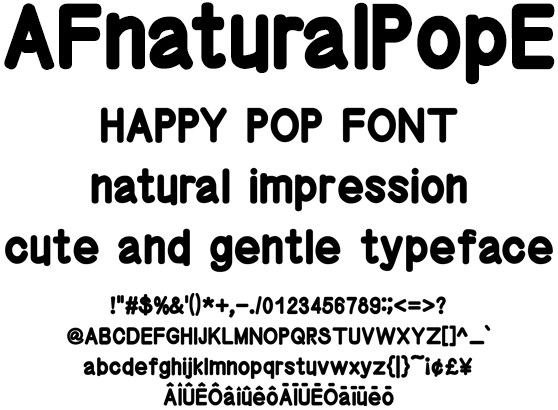
本文用ナチュラルポップ欧文 AFnaturalPopE
AFnaturalPopE
過度な演出を控え丸ゴシックの特徴で柔らかさ優しさを備えたリード・キャプション・本文用ポップ系欧文極太字フォントです。記号類、マクロンやサーカムフレックスなどのダイアクリティカルマーク追加。日本のローマ字表記で使われる訓令式やヘボン式で扱う Ô や Ō を収録、人名地名でもお使い頂けます。